「美味しい(おいしい)!」を表現できる【シズル感】あふれる書体・フォント厳選まとめ
リアル店舗やグルメサイトなどで使える、色々な美味しい味を表現できる和・洋・中の様々な文字(書体・フォント)を厳選してみた。
ちなみに「シズル感」とは、食材や料理を扱った広告写真などの表現において食欲や購買意欲を刺戟するような瑞々しい感覚を意味する言葉。
「まんぷくでもいい、ふとましくそだってほしい。」というそんな願いを込めて、パッケージの文字やメニュー表、お品書きなどの参考に、どうぞ召し上がれ!
ほっこりする美味しい文字(書体・フォント)「クラフト墨」
なんだかほっこりさせる丸っこい墨文字。
甘い文字から居酒屋系の文字を表現できる。
俺のイタリアンや俺のフレンチ、俺のBakeryなどで知られる「俺の株式会社」のロゴ・看板や「吉田類の酒場放浪記」のタイトルロゴとしても有名な人気書体。
美味しい文字「クラフト墨」が「俺の株式会社」のロゴや看板に
美味しい文字「クラフト墨」が「吉田類の酒場放浪記」のロゴに
美味しい文字「クラフト墨」が「塩の花」のロゴに
美味しい文字「クラフト墨」が「和菓子のアン/アンと青春/アンと愛情」のタイトルに
和風の美味しい文字(書体・フォント)「円楷書」
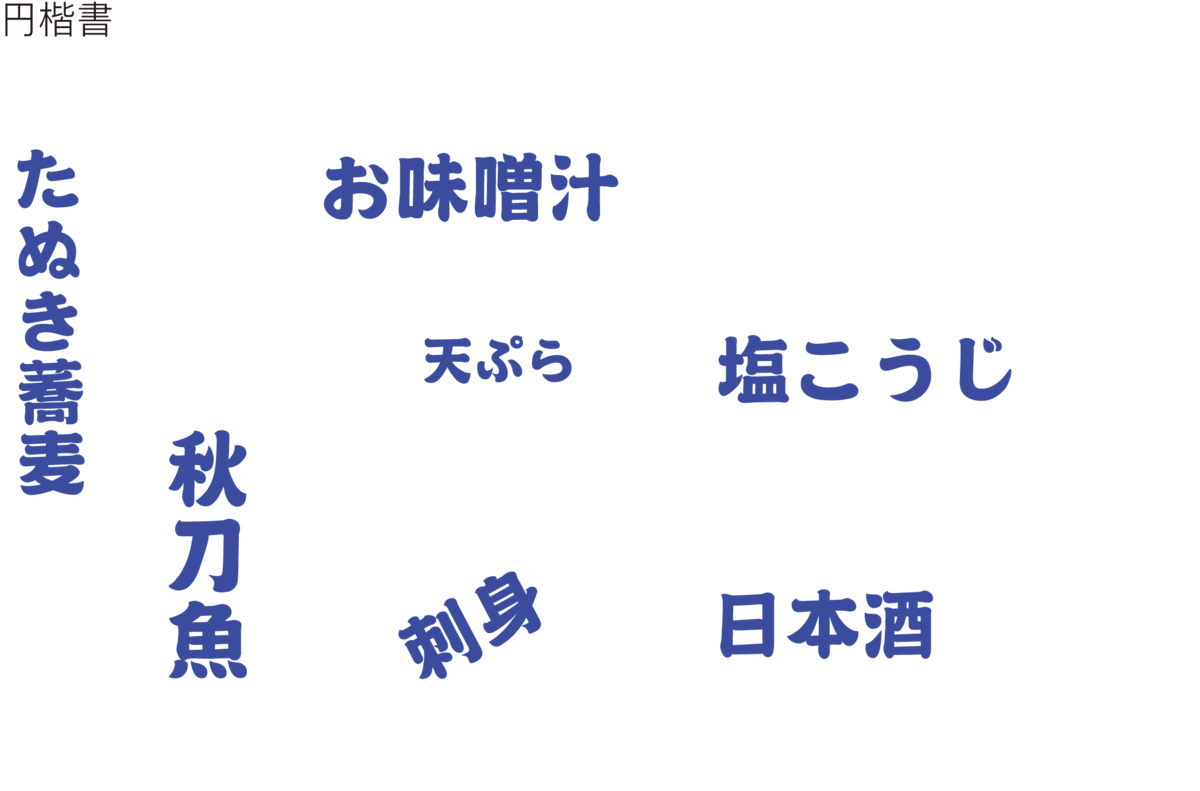
太く丸みのある筆勢により穏やかな一面と力強さを兼ね備えた楷書体。
和風の美味しい文字を表現できる。
美味しい文字「円楷書」が「ハナマルキ 液体塩こうじ」のタイトルロゴに
「ハナマルキ 液体塩こうじ」などハナマルキの「塩こうじ」製品のパッケージタイトルの文字にダイナフォントの円楷書が長体をかけて採用されている。
中華風の美味しい文字(書体・フォント)「唐風隷書体」
横長で太く扁平な字形がどっしりと落ち着きを感じさせる隷書体。
中華風の美味しい文字を表現できる。
レトロな喫茶店などでも使えそうな洋風の美味しい文字(書体・フォント)「琺瑯看板体」
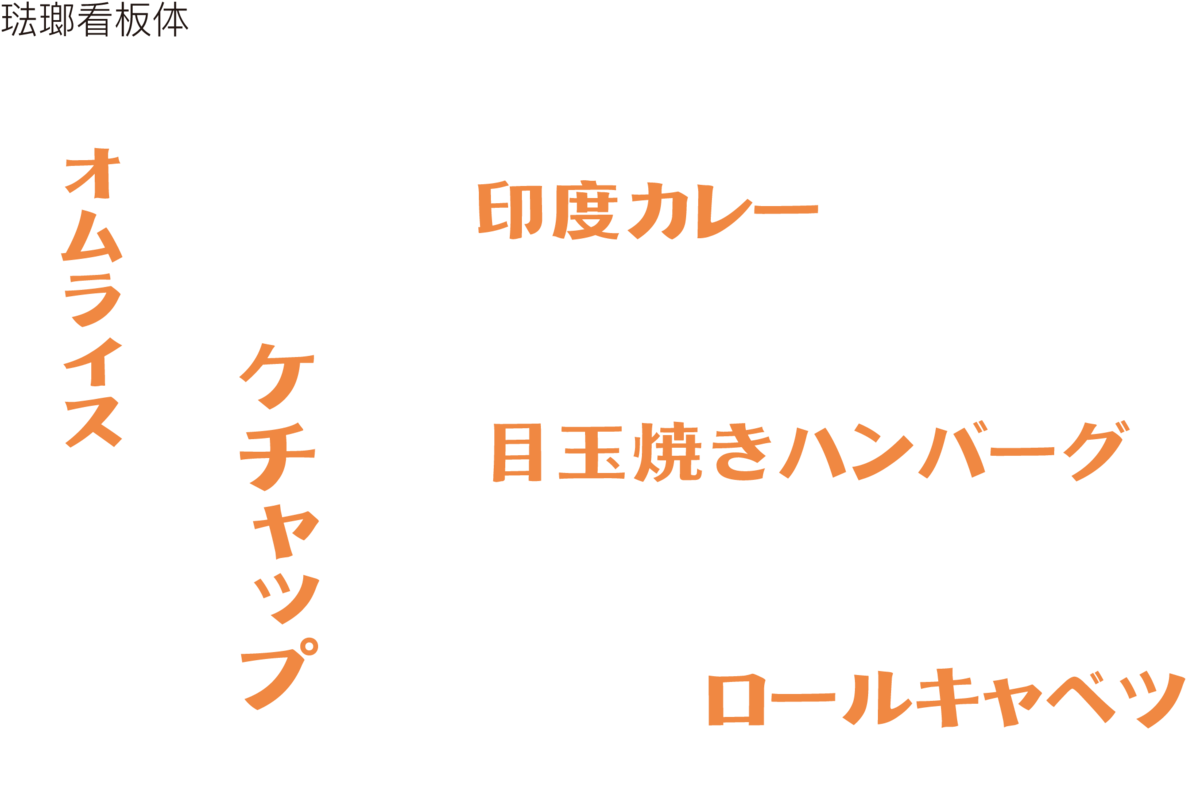
円盤録音機で再生した黒い円盤のイメージと琺瑯看板文字をヒントに昭和の文字印象を応用したレトロ間あふれる書体。
レトロな喫茶店などでも使えそうな洋風の美味しい文字を表現できる。
欧風、エスニック風の美味しい文字(書体・フォント)「欧風花体」
リズミカルな筆遣いの文字にループが特長的な書体。
名前のとおり欧風やエスニック風の美味しい文字を表現できる。
思わず火を噴く程の辛い文字(書体・フォント)「龍門石碑体」
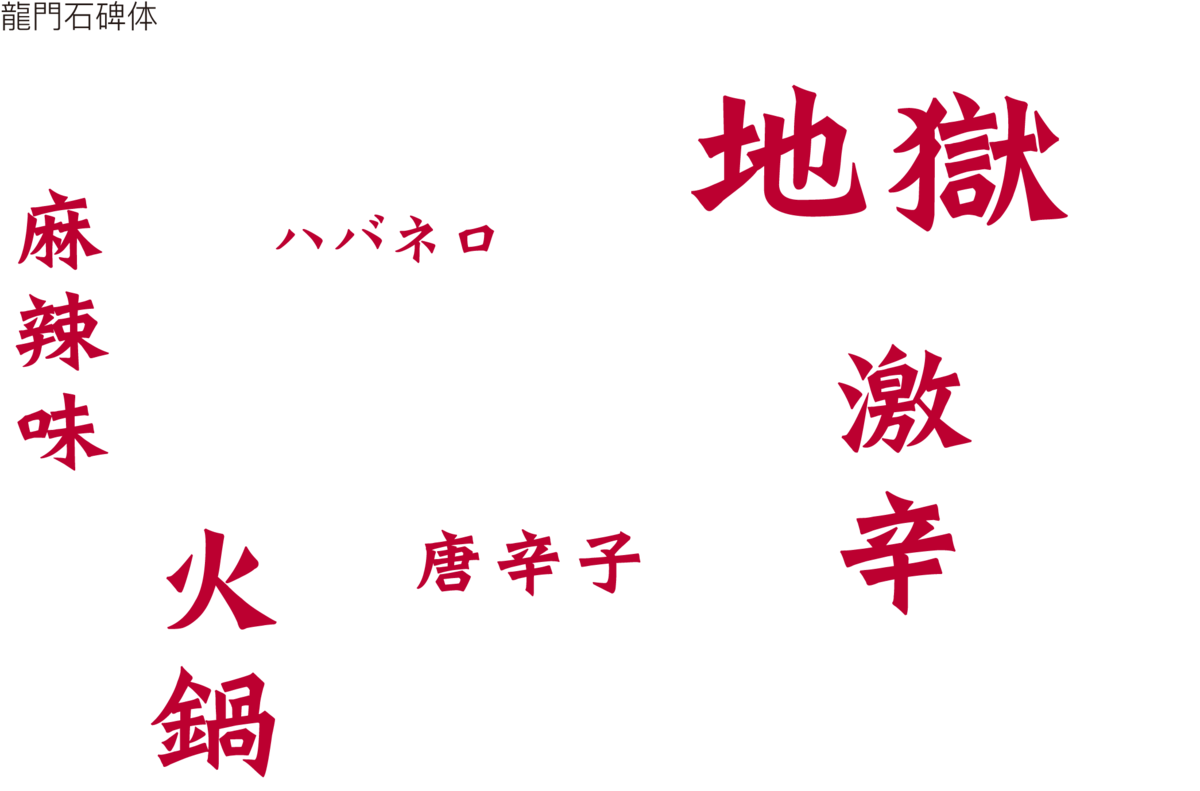
中国の龍門石窟に刻まれた力強く独特の風格を備え北魏の名品と言われているその文字をもとにした書体。
思わず火を噴く程の辛さ(激辛)を表現できる。
スイーツなどより甘くする説がある文字(書体・フォント)「ロマン雪」
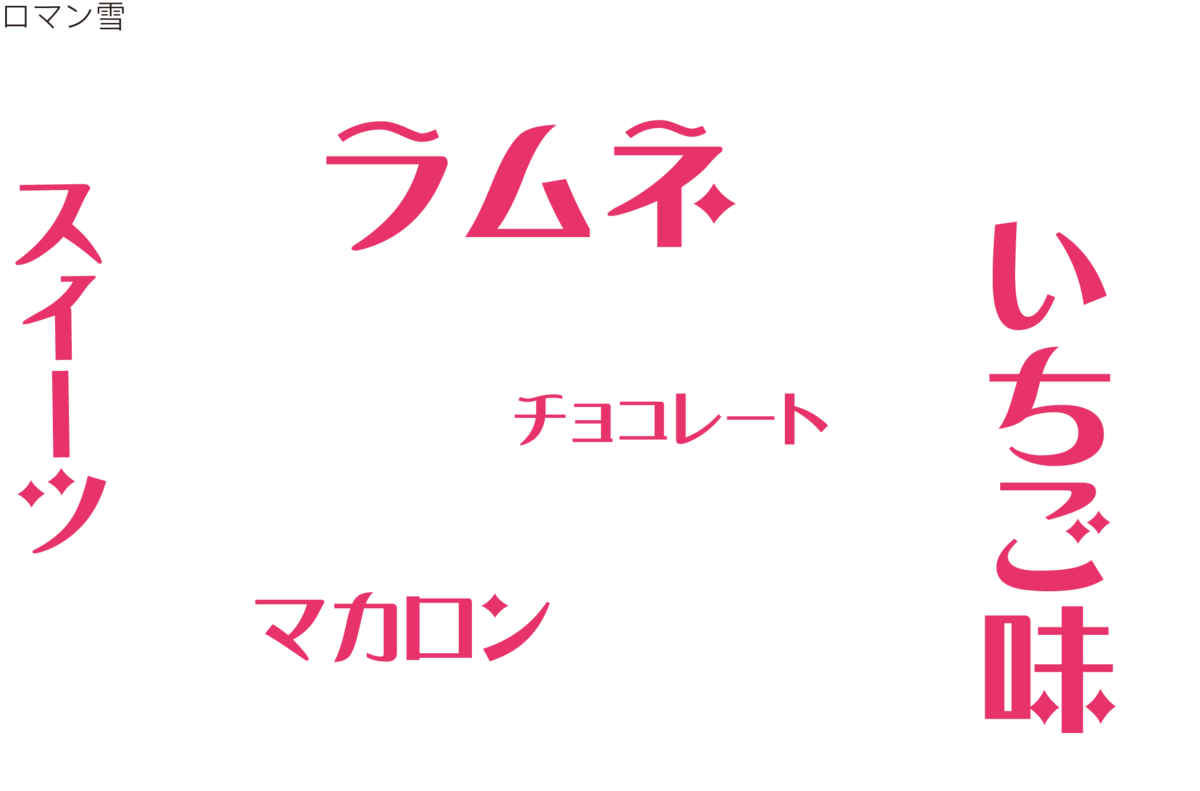
図案化せる実用文字から着想を得て、図中の婦人の華麗な装いや愛らしいスタイルをヒントに古典ロマンの雰囲気を再現した書体。
スイーツなどより甘く表現できる説。
南国感あふれる美味しい文字(書体・フォント)「麗雅宋」
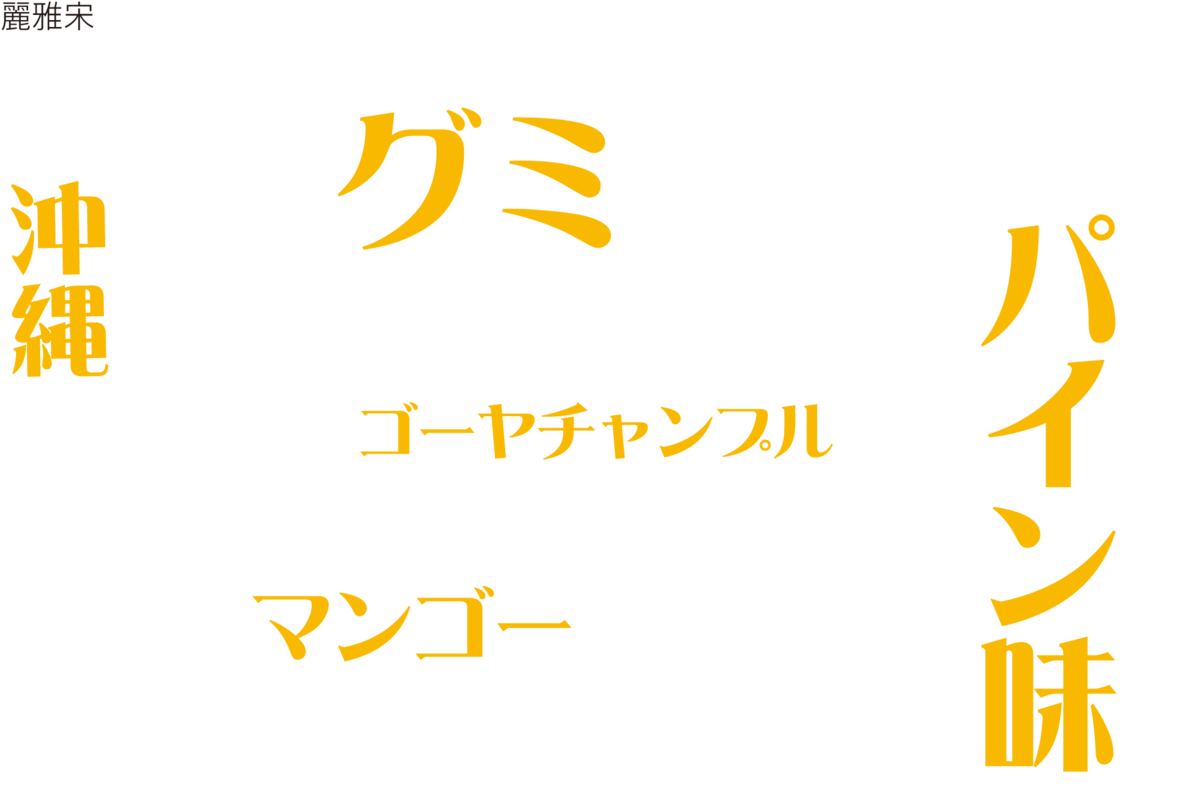
明朝体のストロークに独特なアレンジを加えた書体。
食べ物のパッケージでよく見かける。
特に沖縄や南の島の食べ物が似合う文字。
Cafe&Barなどのムードにあふれた美味しい文字(書体・フォント)「ロマン輝」
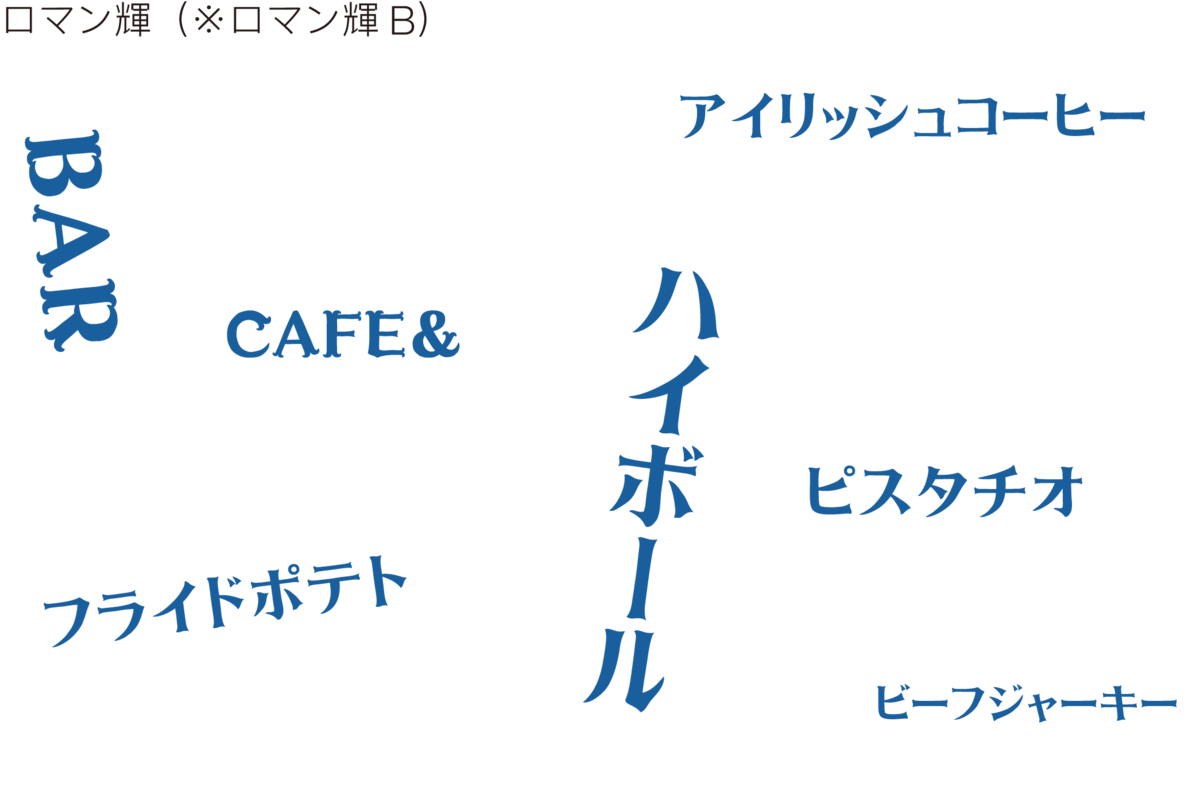
縦画、横画、左はらい、右はらいなどのエレメント中に欧風装飾が加えられた書体。
欧風装飾により、欧州料理などに似合う文字。
ムードも感じさせるデザインはCafe&Barにも適している。
美味しい文字「ロマン輝」が話題の「かじるバターアイス(棒)」のパッケージタイトルの文字に
赤城乳業の開発・販売でSNSで大きな話題を呼んでいる「かじるバターアイス(棒)」のパッケージタイトルの文字に「ロマン輝」が使用されている。
ちなみに使用されているの「ロマン輝B」の方となる。
美味しい文字「ロマン輝」が丸福珈琲店監修ファミリーマート「濃いコーヒーバウムクーヘン」「濃いコーヒースティックパウンドケーキ」のタイトルに
丸福珈琲店監修ファミリーマート「濃いコーヒーバウムクーヘン」「濃いコーヒースティックパウンドケーキ」のタイトルにロマン輝が使用されている。